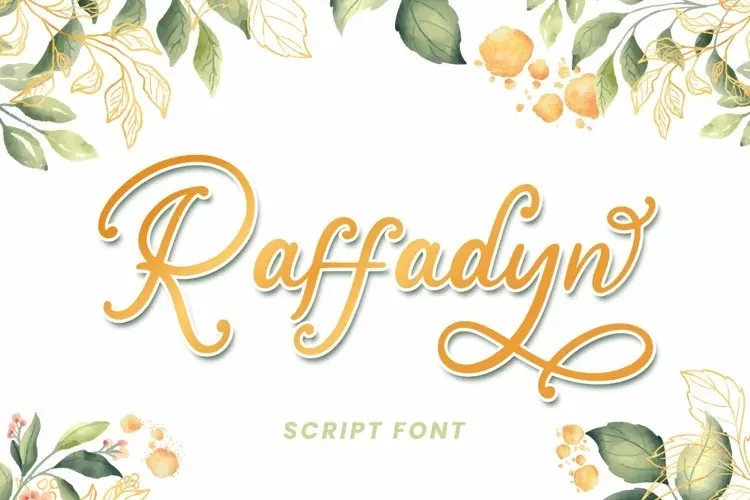
A Raffadyn Font é uma elegante tipografia script desenvolvida por Attype-Studio para perfilar seu design perfeito para eventos românticos e singelos como casamentos. Com sua característica refinada, ela se destaca ao combinar a Raffadyn com setes estilizadas para criar fontes de escrita para casamentos incríveis! O estilo versátil desta fonte irradia um amor incontrolável, tornando-a uma escolha excepcional para quem deseja adicionar um toque especial a qualquer design. Perfecto mesmo não é?